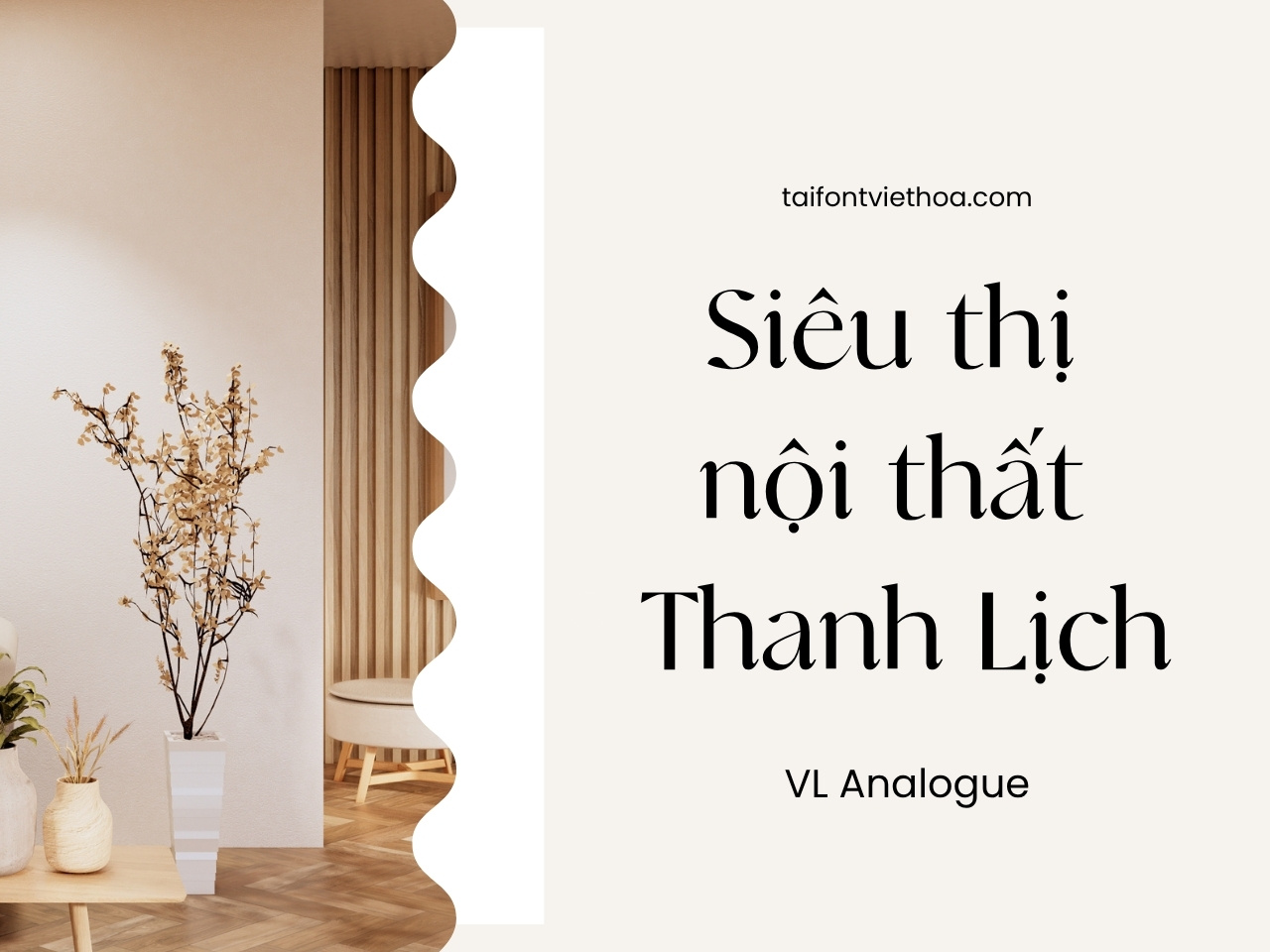
Font việt hóa VL Analogue đầy đủ
Tác giả Font: Analogue
Giới thiệu về font VL Analogue
VL Analogue là một font serif hiện đại mang cảm hứng cổ điển, được thiết kế với tỷ lệ chữ thanh lịch và kết cấu chân chữ rõ nét. Font gốc đến từ hãng Studio Sun – một nhà sáng tạo font nổi bật với những bộ chữ tinh xảo dành cho branding cao cấp. Phiên bản Việt hóa trọn bộ do Font Việt Linh thực hiện, hỗ trợ đầy đủ tiếng Việt với hệ thống dấu được tinh chỉnh kỹ lưỡng. Ngoài tiếng Việt, font còn tương thích với hơn 60 ngôn ngữ khác thông qua bảng mã Latin Extended. Font đã được taifontviethoa.com chọn lọc và ứng dụng thực tế cho nhiều dự án nhận diện thương hiệu, thiết kế in ấn và truyền thông cao cấp tại Việt Nam.
Đặc điểm thiết kế và ứng dụng của VL Analogue
VL Analogue có thiết kế tinh tế, các đường nét mảnh và dứt khoát, độ tương phản giữa nét dày và mảnh rõ rệt, tạo nên sự sang trọng và chuyên nghiệp. Font gồm nhiều trọng lượng, phù hợp cho cả tiêu đề lớn lẫn văn bản nội dung. Phong cách của font là sự kết hợp giữa tính cổ điển và hiện đại, giúp nó thích hợp trong cả in ấn và giao diện kỹ thuật số.
Font phù hợp với thiết kế logo thương hiệu cao cấp, bìa sách, tiêu đề tạp chí, danh thiếp, bao bì mỹ phẩm, bộ nhận diện ngành nội thất, và các ấn phẩm marketing mang tính tinh tế. Ngành nghề nên ứng dụng gồm: thời trang, mỹ phẩm cao cấp, xuất bản, bất động sản, thiết kế nội thất và truyền thông sáng tạo.